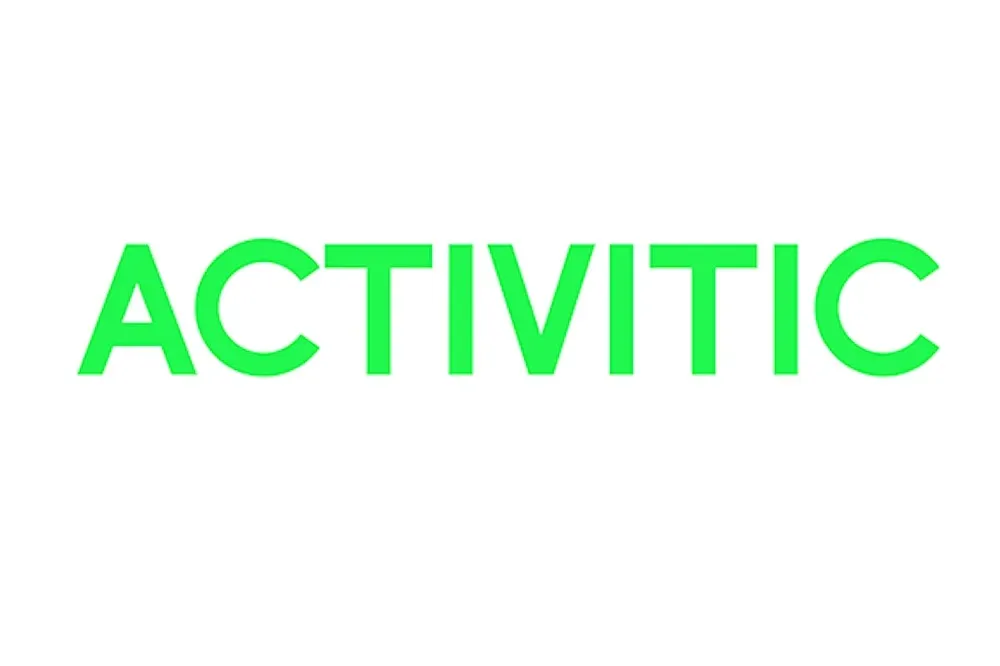
A fonte Activitic é uma escolha ideal para quem busca simplicidade e elegância em seu design. Desenvolvida pelo talentoso designer Joel M., essa fonte sans-serif é minimalista e limpa, com duas opções de estilo – Regular e Cut. Suas características únicas permitem que seja usada não apenas para texto padrão ou corpo do texto, mas também para headlines e títulos, garantindo uma forte presença visual em qualquer projeto. Seja você criando anúncios altamente atraentes, desenvolvendo material de marketing digital ou simplesmente estilizando seu site, a Activitic estará certamente ao seu lado, oferecendo um conjunto de ferramentas versáteis e elegante para tornar seus projetos ainda mais agradáveis aos olhos do público.